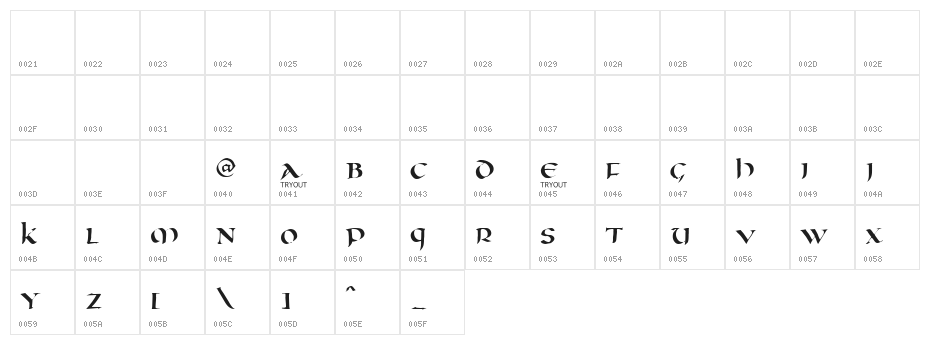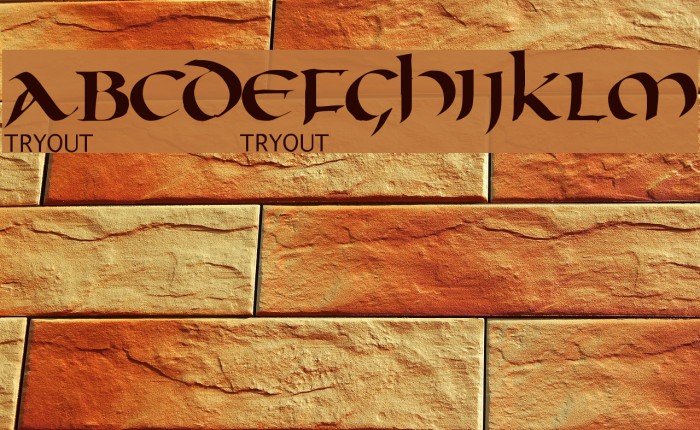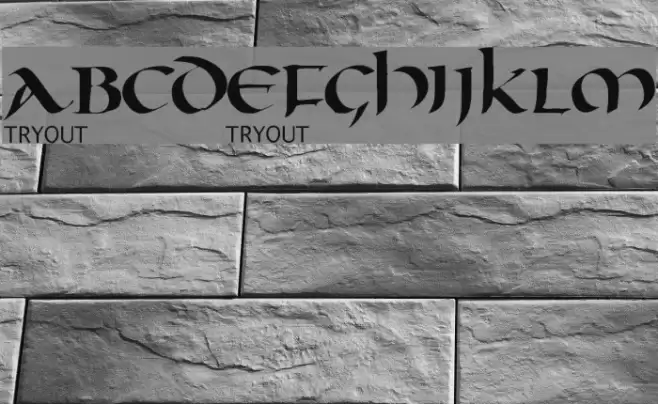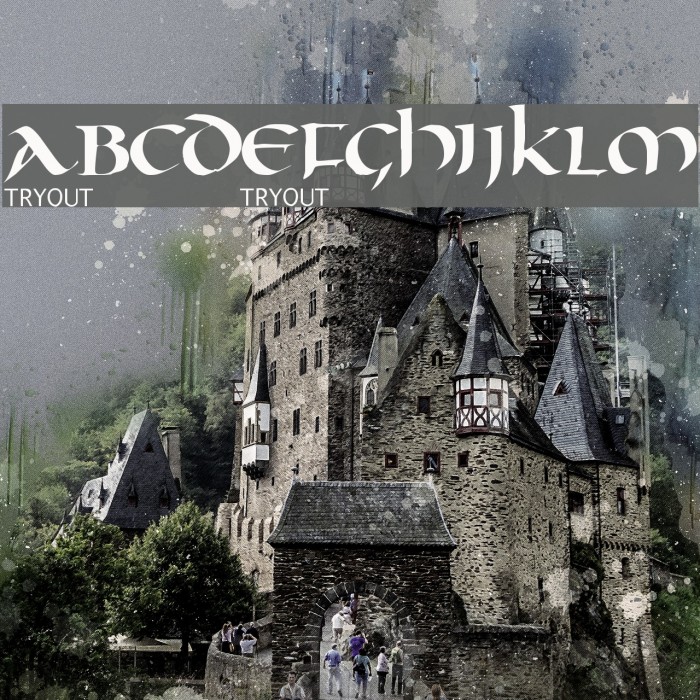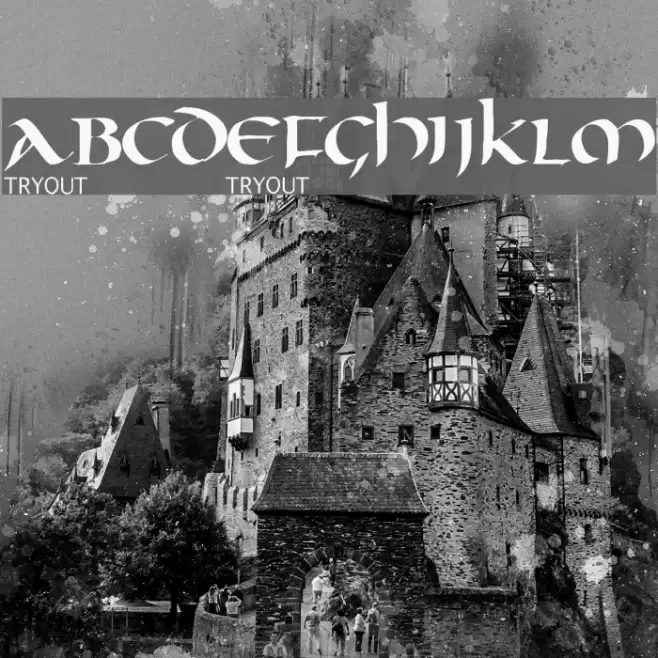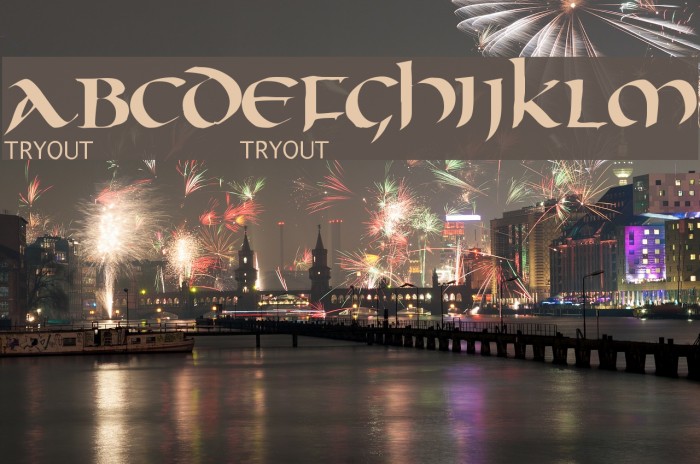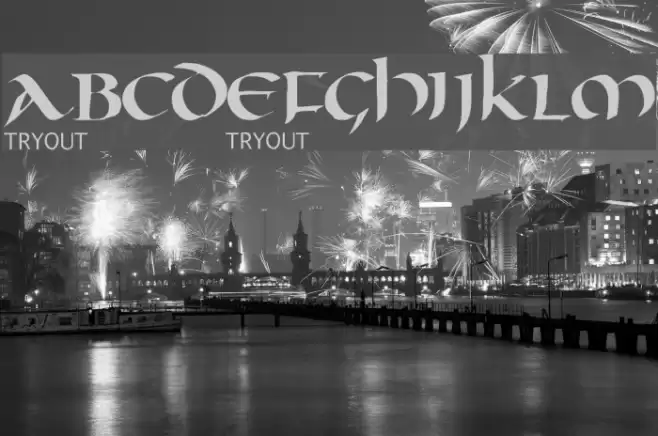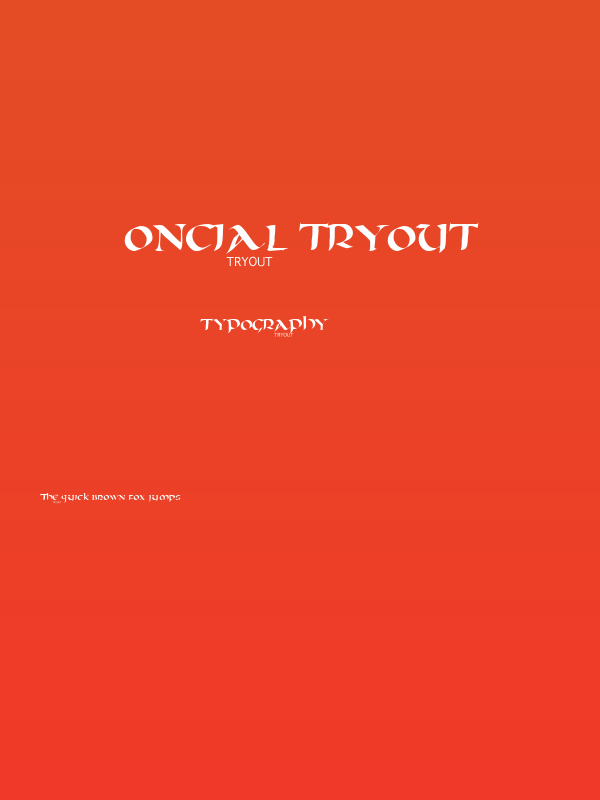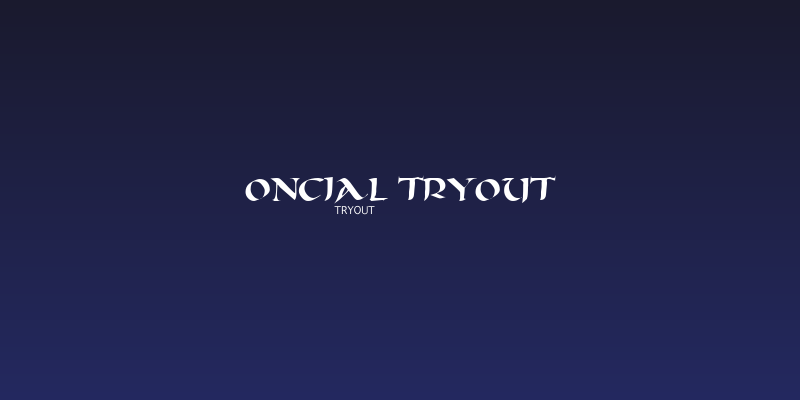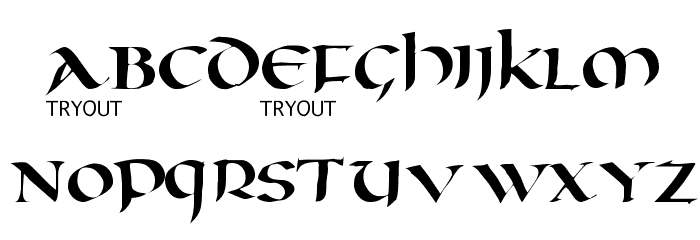
Oncial Tryout Font
| श्रेणियाँ | Script |
| कंट्रास्ट | High |
| समग्र शैली | Vintage |
| उपयोग का मामला | Headlines, Logos |
| सुझाए गए प्रोजेक्ट | Ideal for projects that require a historical or fantasy theme, such as book covers, movie posters, or themed event invitations. |